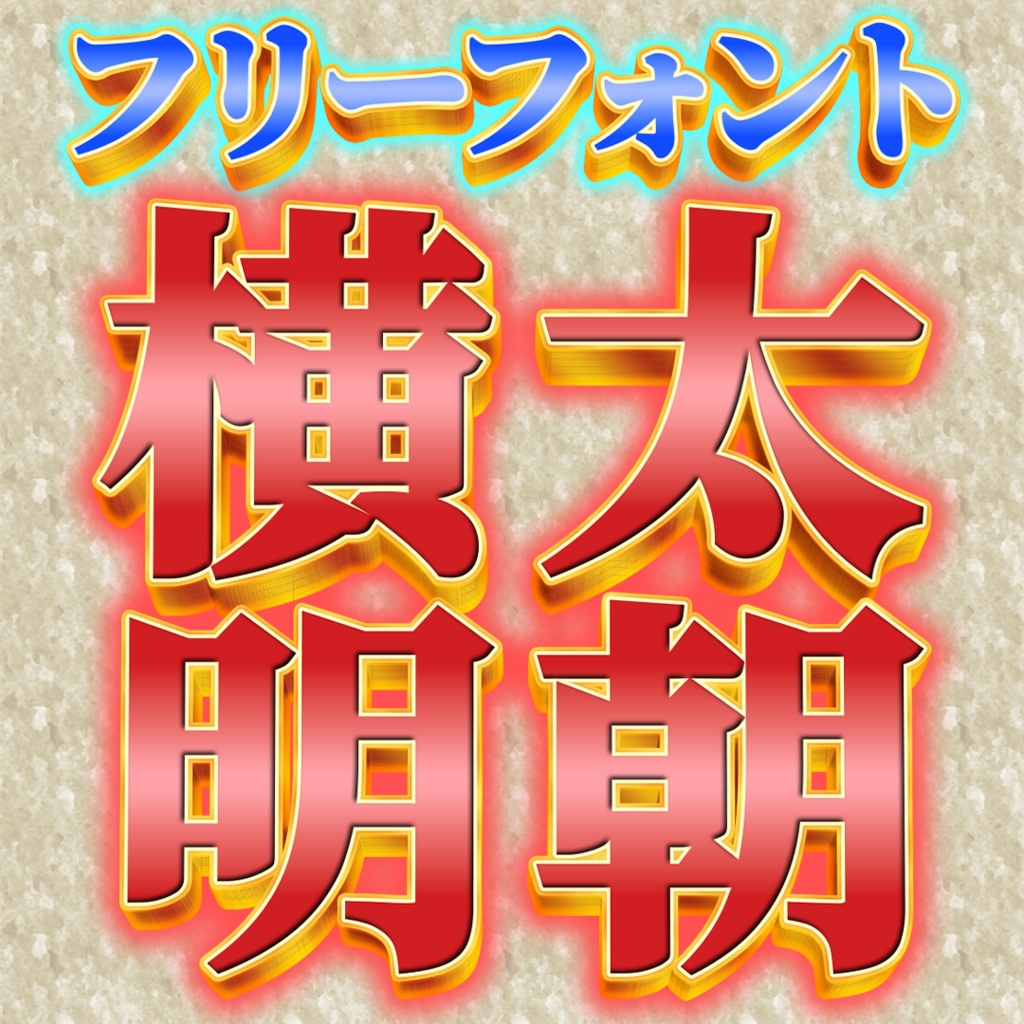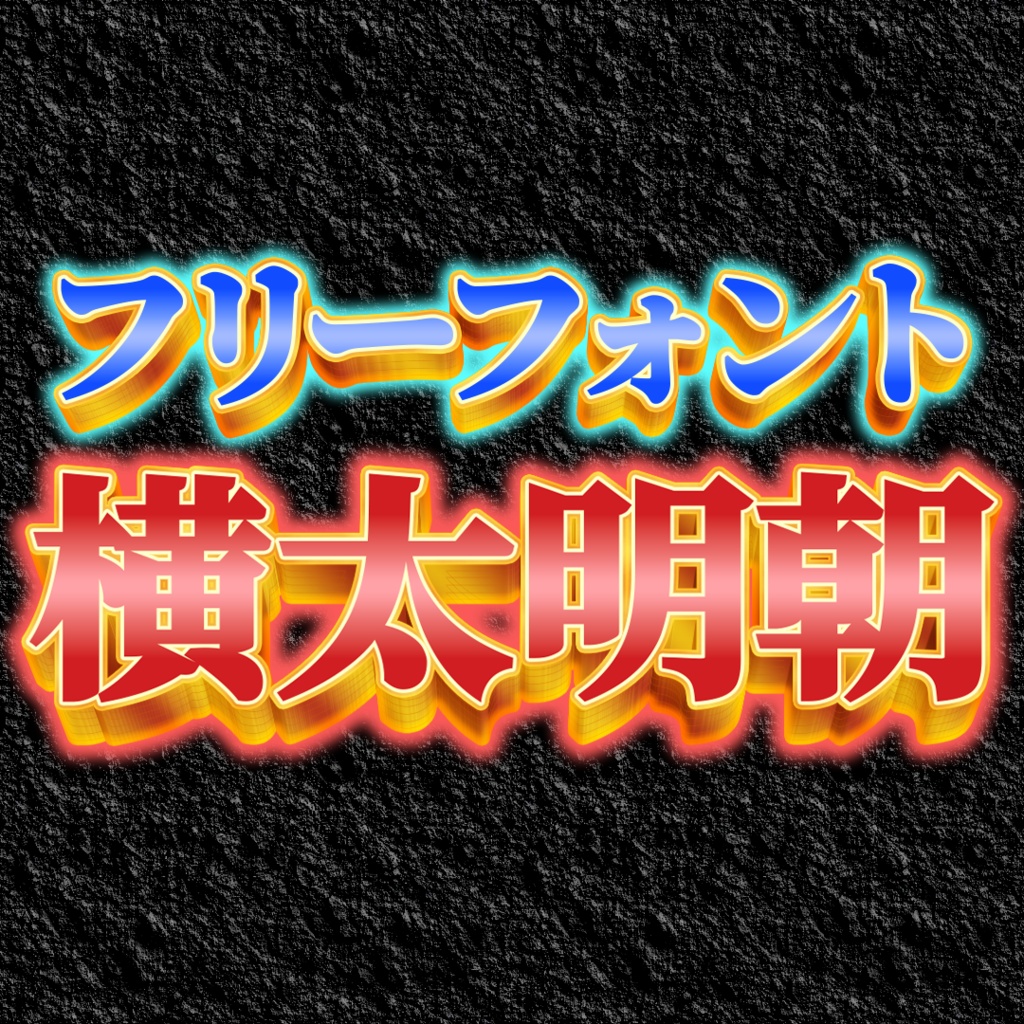
横太明朝【フリーフォント】
横太明朝 「Noto Serif JP」を横太加工したフォントです。 機械的に処理している都合上、潰れている文字が見受けられますのであらかじめご了承ください。 中身は同じですが、投げ銭版もございます。ご支援いただけましたら幸いです。 ライセンス 当フォントはSIL Open Font License1.1の下で公開いたします。 個人利用・商用利用にかかわらず無償で使用可能です。 SILライセンスにつきましては以下をご確認ください。 ライセンス原文 http://scripts.sil.org/OFL ライセンス原文日本語サイト https://licenses.opensource.jp/OFL-1.1/OFL-1.1.html ライセンスざっくり解説 https://tanukifont.com/sil/ 免責事項 当フォントの使用に関しては全て無保証とさせていただきます。 謝辞 全ての関係者の皆様に深くお礼申し上げます。 Noto Serif Japanese https://fonts.google.com/noto/specimen/Noto+Serif+JP 詳細 お問い合わせ等ございましたらBOOTHの「ショップへのお問い合わせ」よりお願い致します。 横太明朝 制作:やっちゃん https://yattyann.booth.pm/ フォント公開・利用規約制定 2026年4月10日